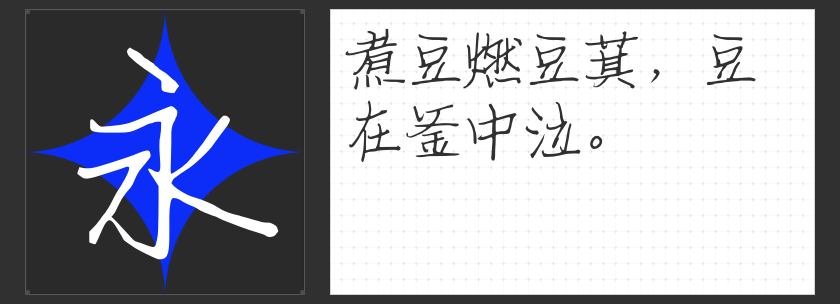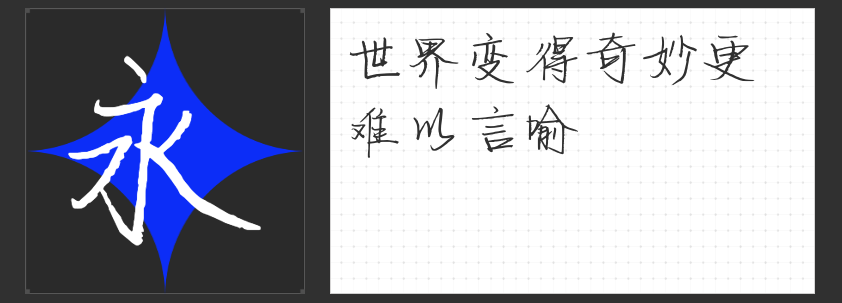
硬笔手写字体精选:赋予设计作品独特魅力
在视觉设计领域,字体选择至关重要。它不仅能够传达信息,更能赋予作品独特的风格和情感。今天,为大家推荐四款硬笔手写字体,它们各具特色,能够满足不同设计需求,让你的作品更加出众。
励字造仲夏简 常规是一款清新文艺与传统相结合的硬笔手写字体。其笔画清晰且坚挺爽利,边缘略带斑驳,展现出手写字的力量和果敢。钩笔处理随意洒脱,赋予了字体独特的韵味。字型端正,通用性强,可广泛应用于商业海报、包装设计、短视频制作以及新媒体等多个领域。这款字体不仅能够提升作品的视觉效果,还能传达出清新脱俗的品牌形象。
字青春悸动简 常规字形结构端正,笔画清晰,整体风格清秀别致。这款字体给人一种年轻、活力的感觉,非常适合用于短视频标题、海报文案等场合。其应用范围较广,能够轻松融入各种设计风格,为作品增添一份青春气息。
MyFont恋爱偷着乐简 细体是一款自由、个性的手写字体,娟秀而整齐。这款字体适合多字排版,辨识度高,实用性强。无论是用于社交媒体文案、产品包装还是广告海报,都能迅速吸引观众的注意力,传达出温馨、浪漫的情感氛围。
MyFont未来简 细体笔画之间呼应强烈,露锋起笔,展现出凌厉、潇洒的风格。这款字体流畅飘逸,给人一种未来感十足的感觉。非常适合用于科技产品宣传、时尚品牌海报等场合,能够凸显出作品的创新精神和前沿感。
综上所述,这四款硬笔手写字体各具特色,能够满足不同设计需求。它们不仅能够提升作品的视觉效果,还能传达出独特的情感氛围。赶快尝试它们吧,让你的设计作品更加出众!